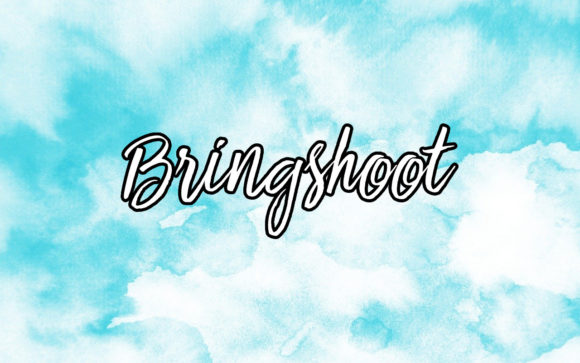
Bringshoot
Si vous recherchez des ressources de haute qualité comme Bringshoot, ce pack premium est un choix fantastique pour vos projets créatifs.
Que vous créiez des produits POD (impression à la demande), des invitations de mariage ou des visuels pour les réseaux sociaux, Bringshoot est un choix idéal.